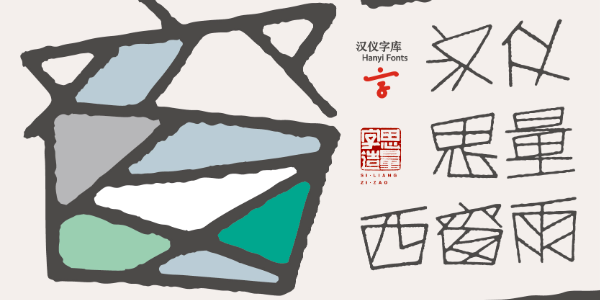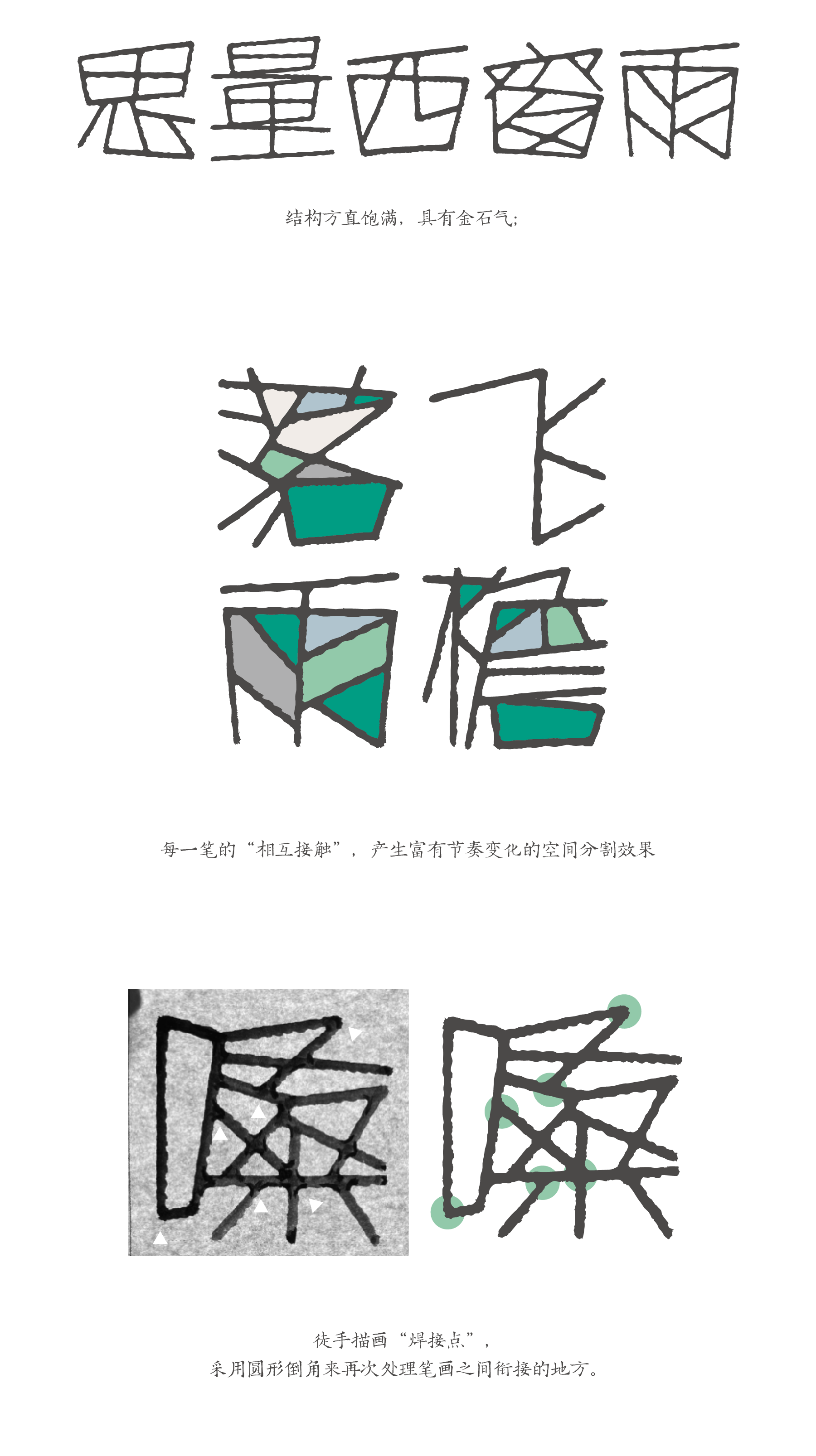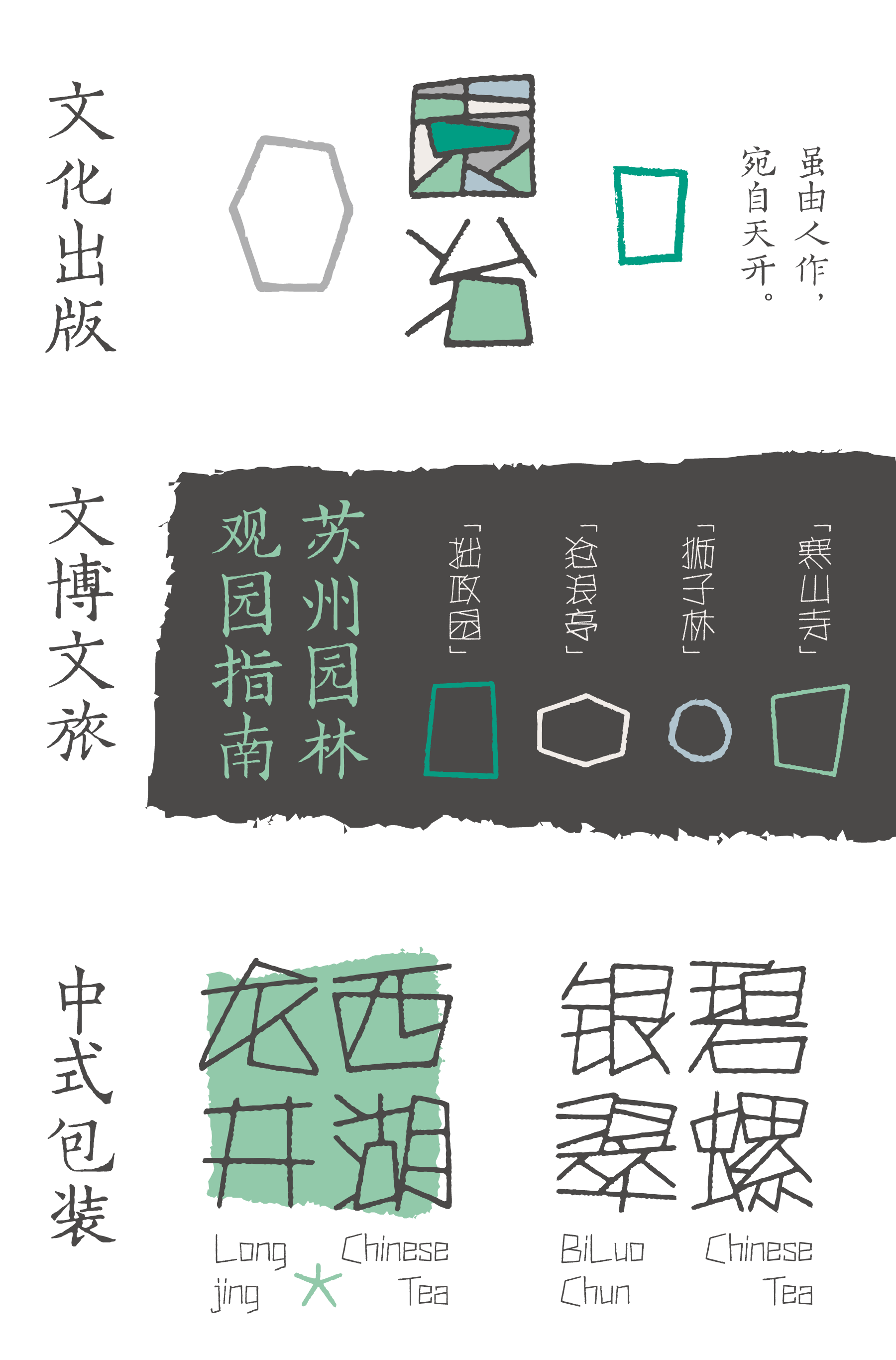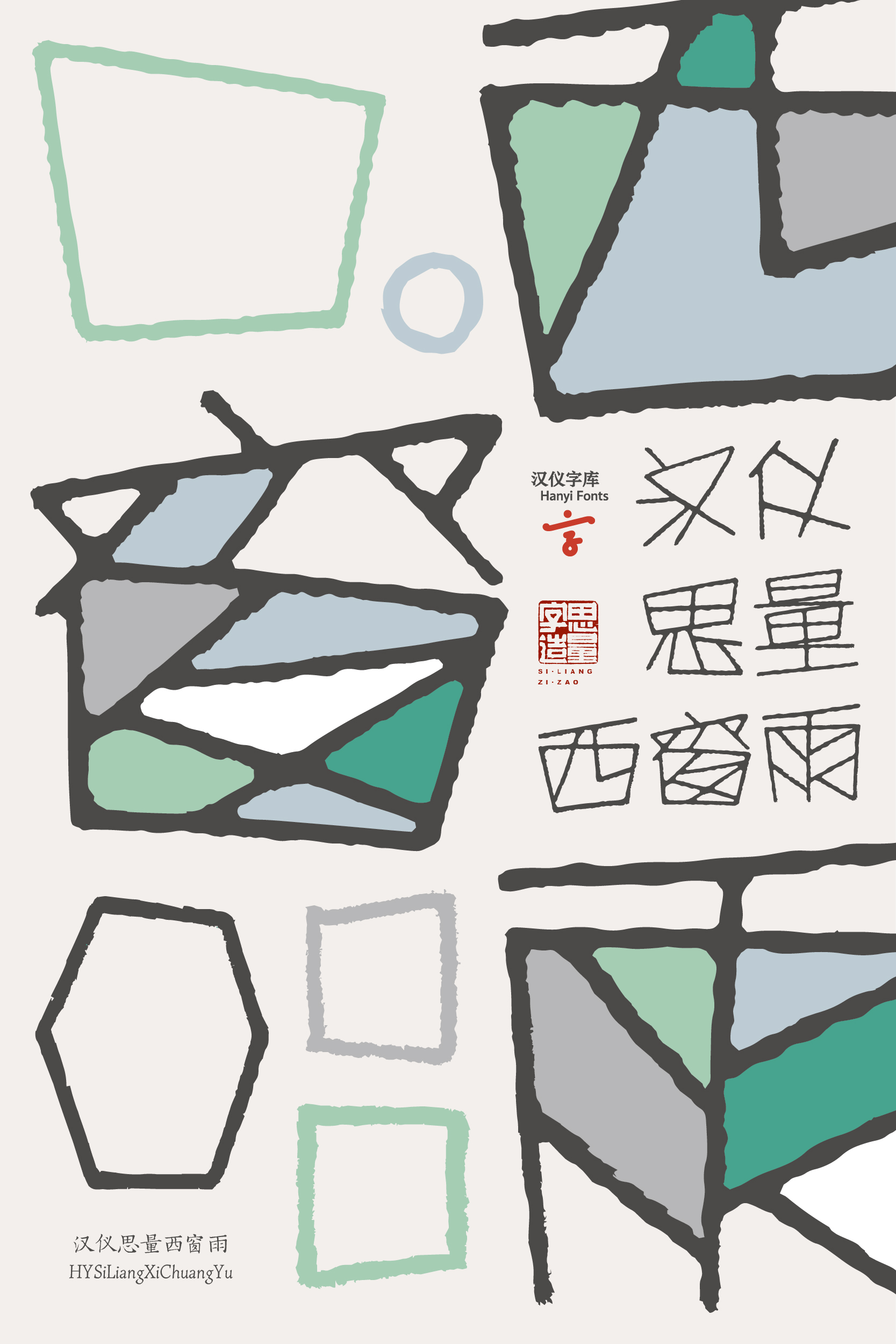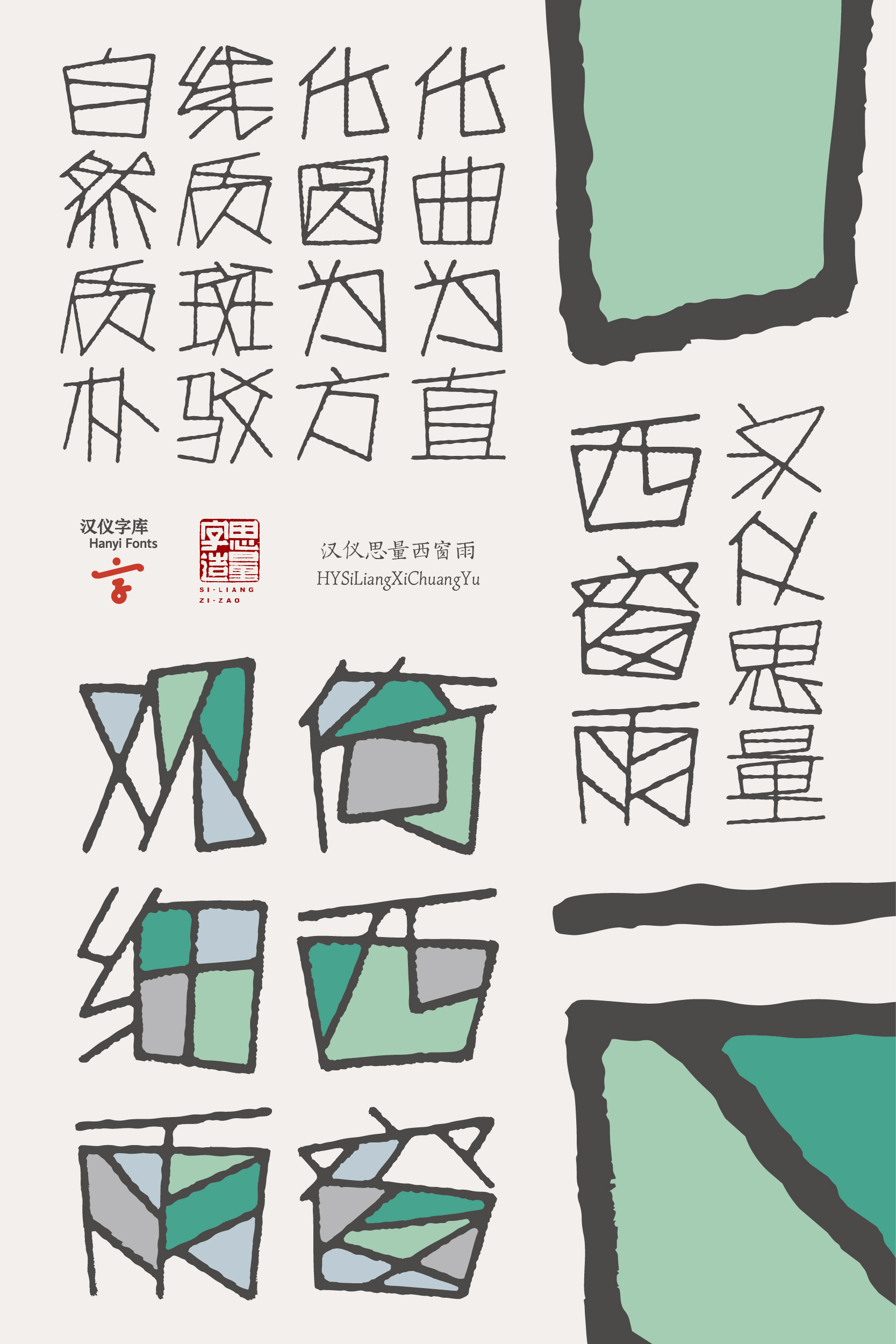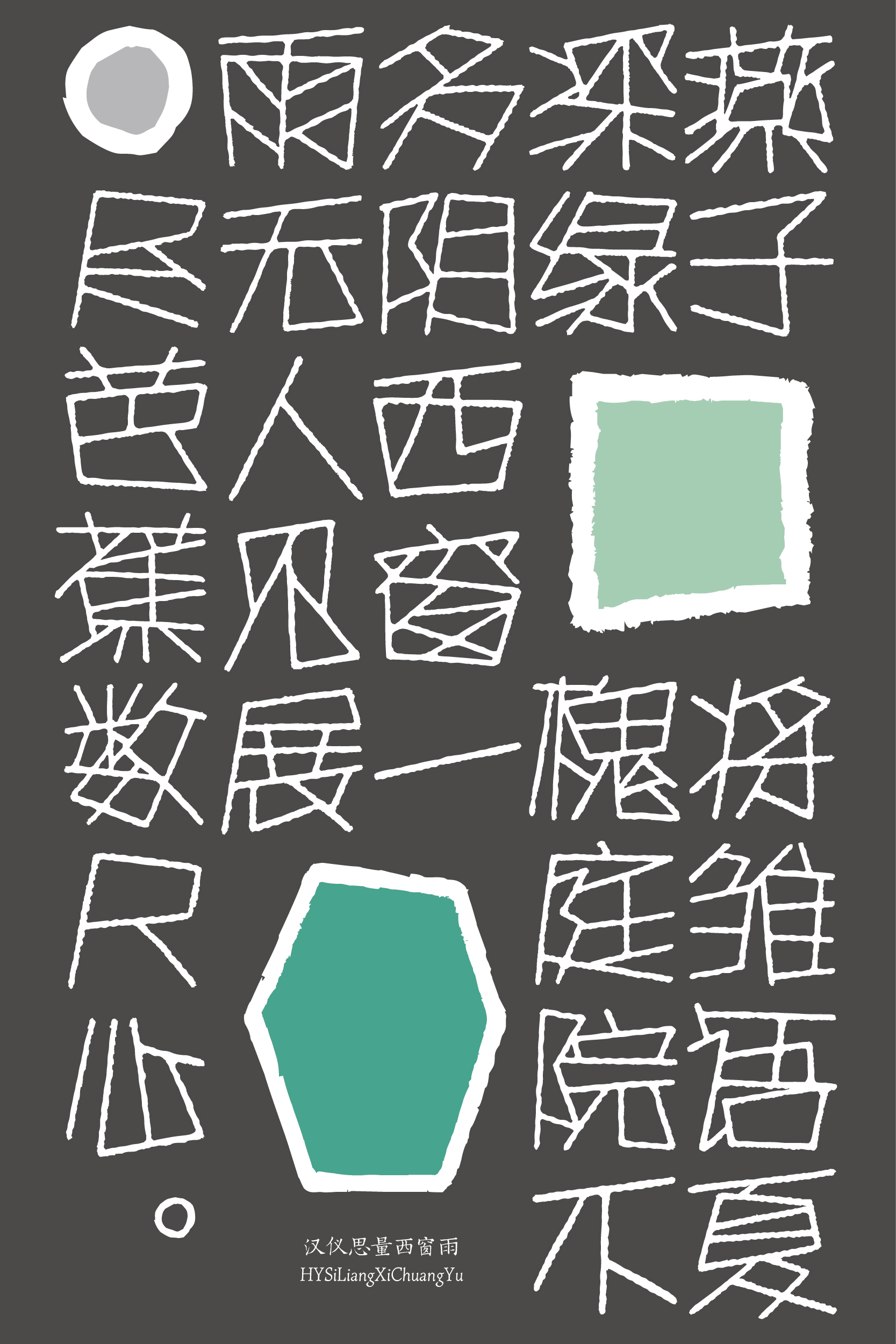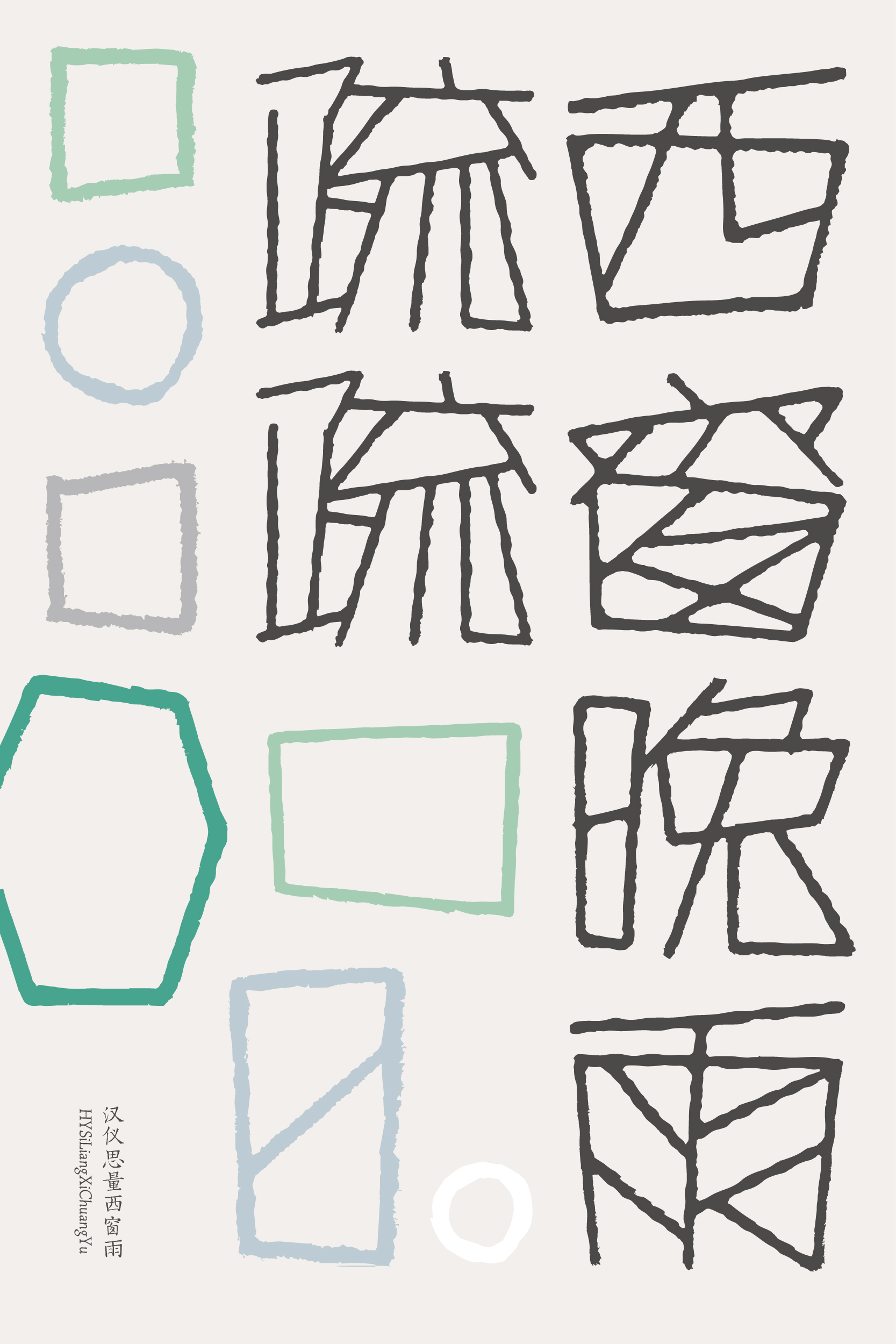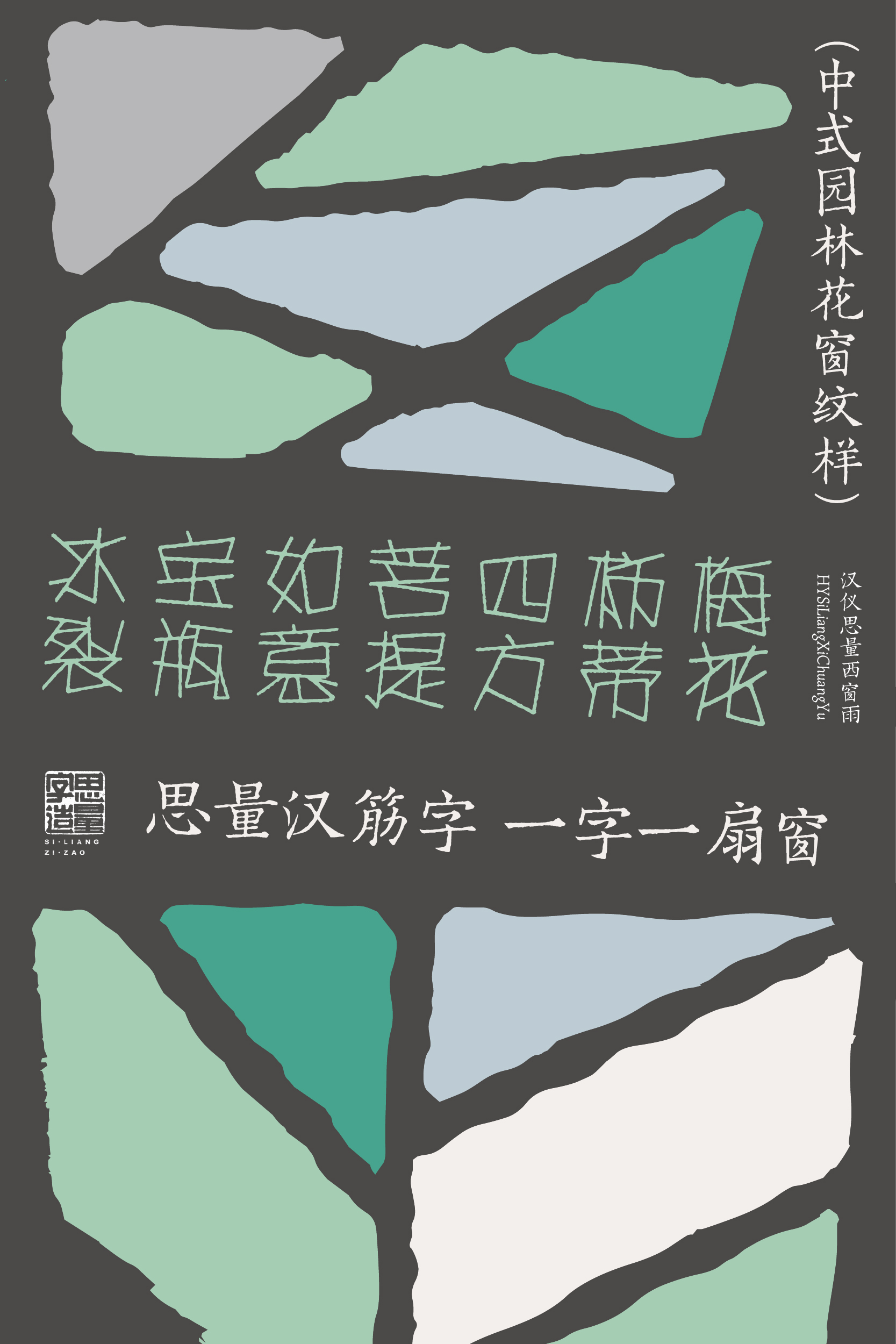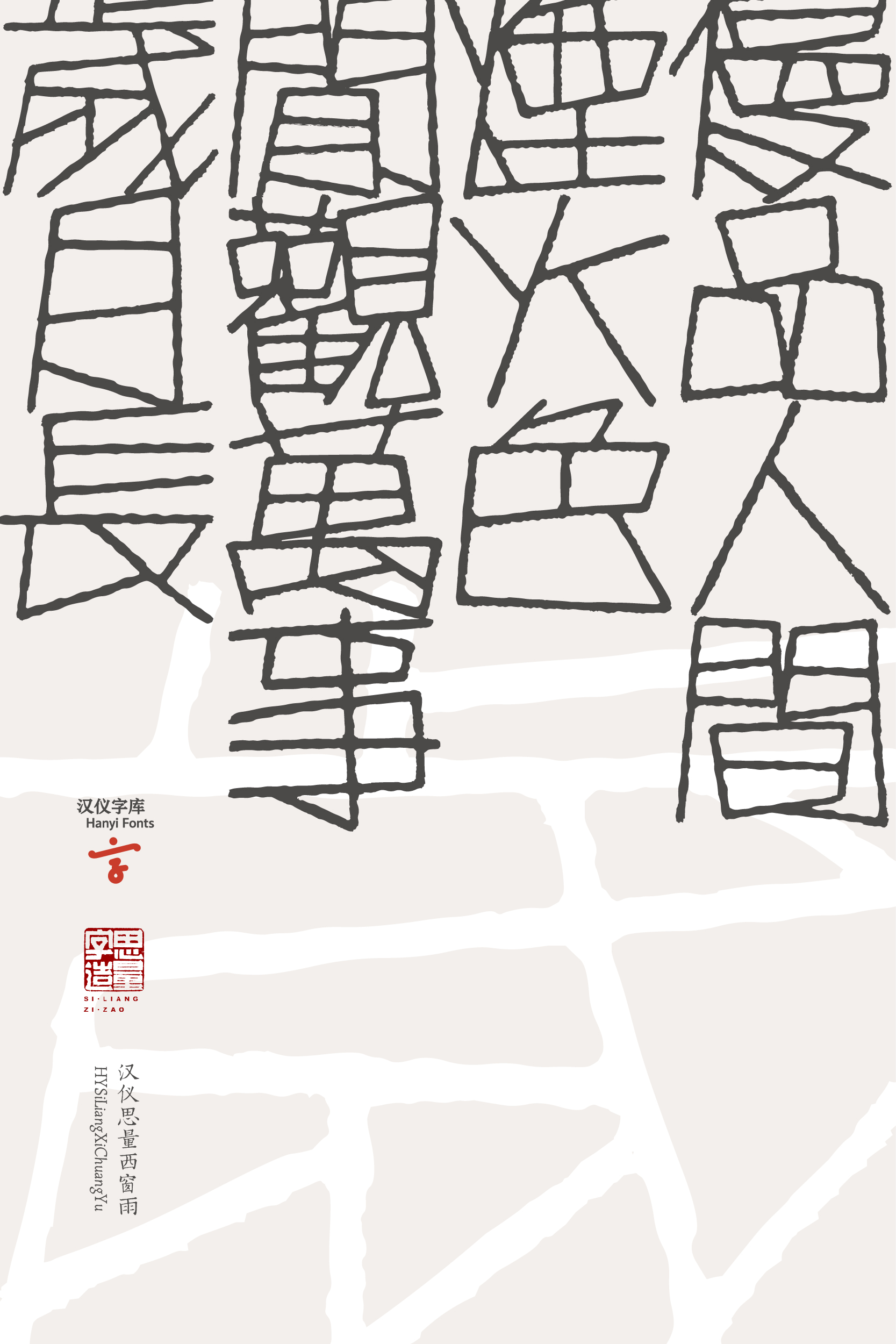
把园林花窗搬进字体里会是什么样?
汉仪思量西窗雨是一款令人联想到园林花窗的创意书写字体,兼具现代几何构成美感。结字有金石气,字形方而满;化曲为直的笔画构成取开合聚散、向背权衡等处理手法,具有空间延伸感,线条排布参考汉代篆刻、瓦当砖文、传统纹样及西方蒙德里安的新造型主义作品,中西合璧;线质斑驳,自然质朴,书写细节丰富。
汉仪思量西窗雨的前身,是作者陈亮参加汉仪字库第二届设计书写展的参赛作品《兰亭序》。作者通过不同的构成要素、笔墨工具进行书写,其中包括线条本身的直曲、粗细变化,也有用笔上的缓疾、顺逆,同时还会兼顾纸张上的生熟,墨色上的浓淡等。
作者以传统技巧为基础,从中国传统汉代石刻、碑刻砖文、园林窗花、冰裂纹瓷器等汲取灵感,又融合西方以蒙德里安为代表的构成主义作品。并与汉仪字库产品研发中心反复讨论、修改字稿方向,最终落在“东方传统园林花窗× 西方现代几何构成”的字库产品定位。
汉仪思量西窗雨,结字有金石气,方而满;取开合聚散、向背权衡等处理手法,具有空间延伸感;遵循此字体“笔笔相接闭合”的构字原理,斟酌出最佳的分割方案,用笔画将字切割成大小不一、富有节奏变化的空间。
“直线”是本字体的唯一构字“原材料”,以小号毛笔略带绞锋书写,尽量保证每一根线条都略微不同,甚至有笔势之间递进的关系。
这款字体的排版效果独具装饰图案的意味,推荐作为标题或放大字形用于装饰,与中式传统园林造景十分相称,适合用于传统文化艺术、文博文旅、新中式品牌等场景。